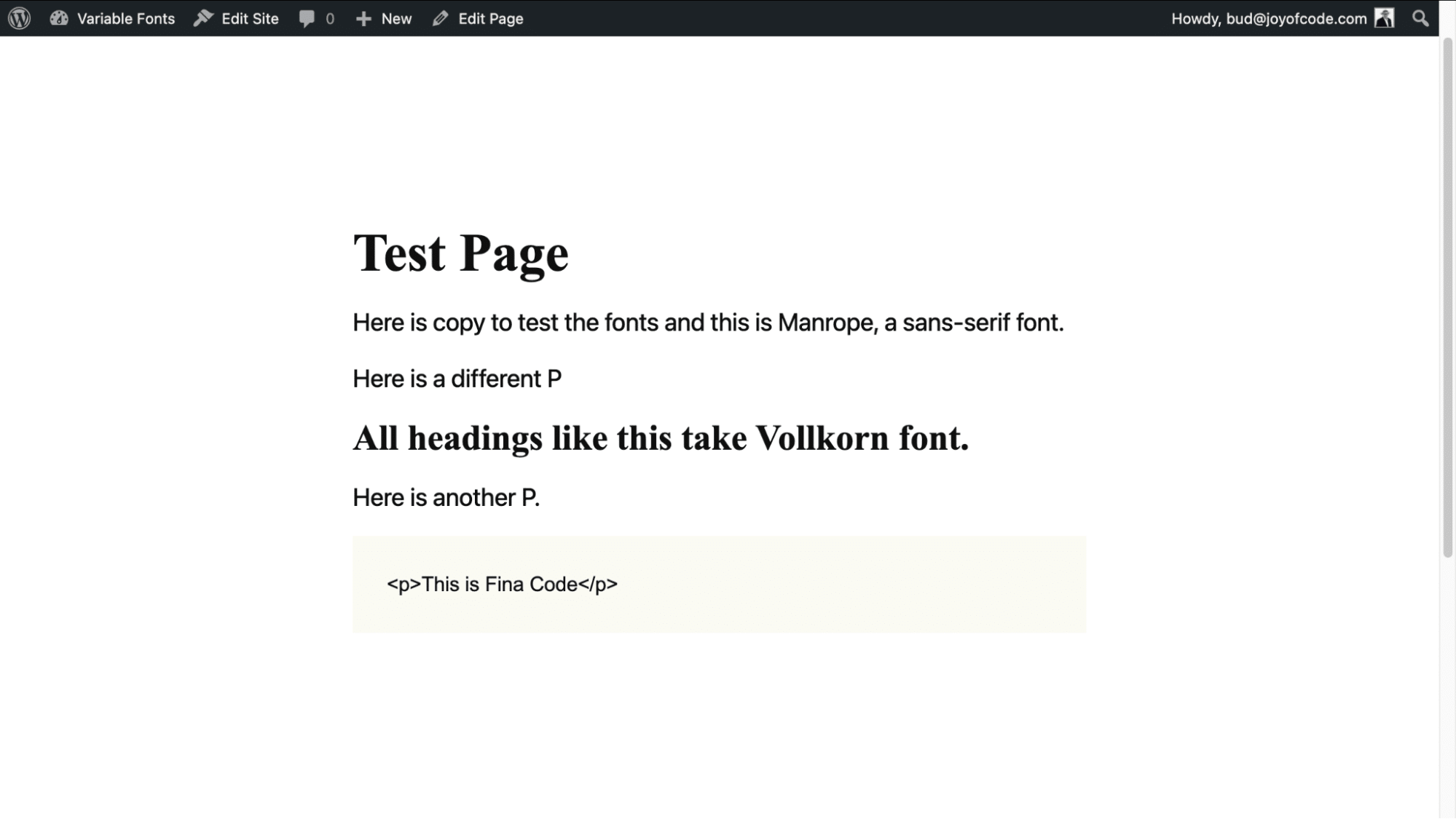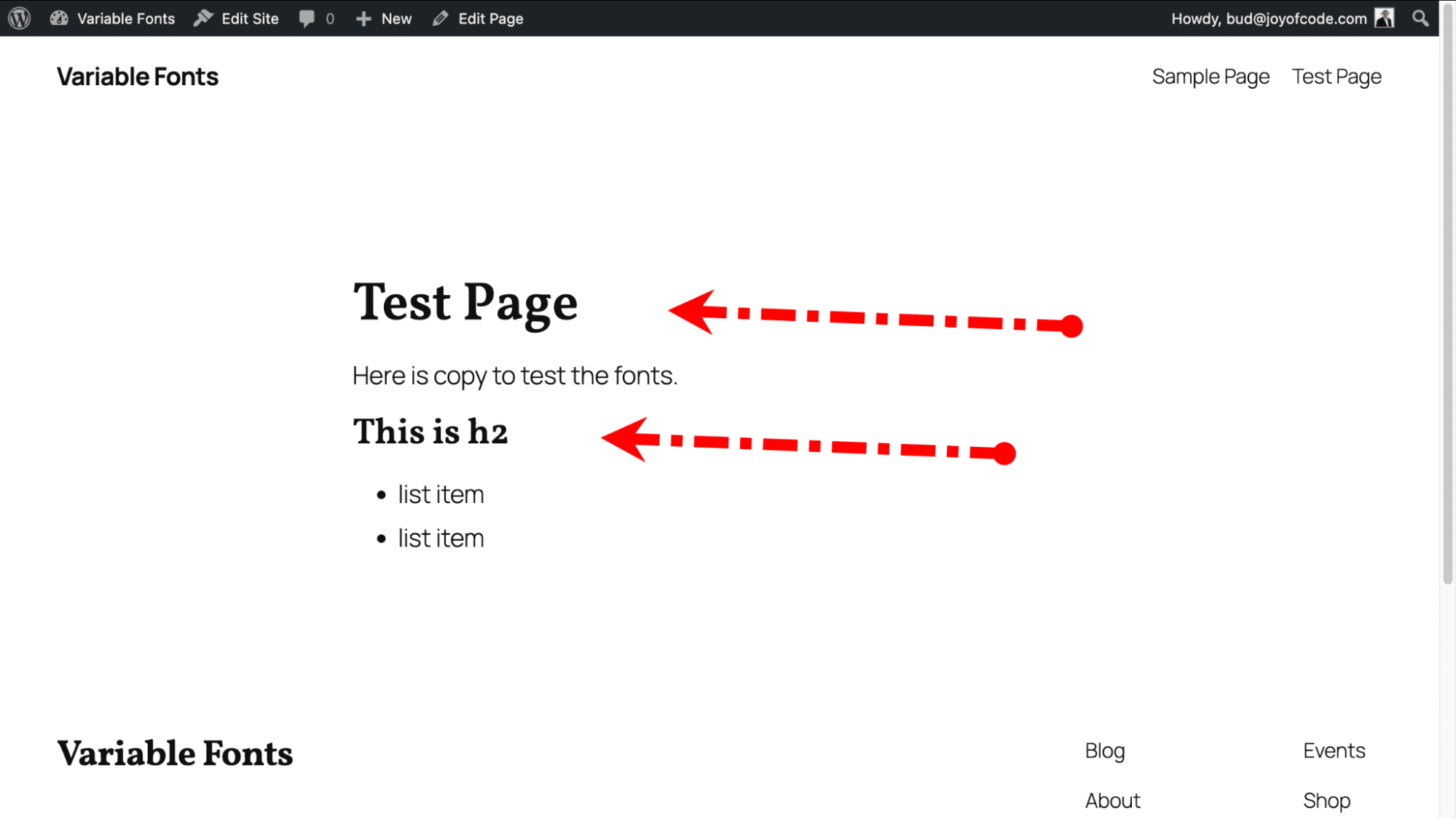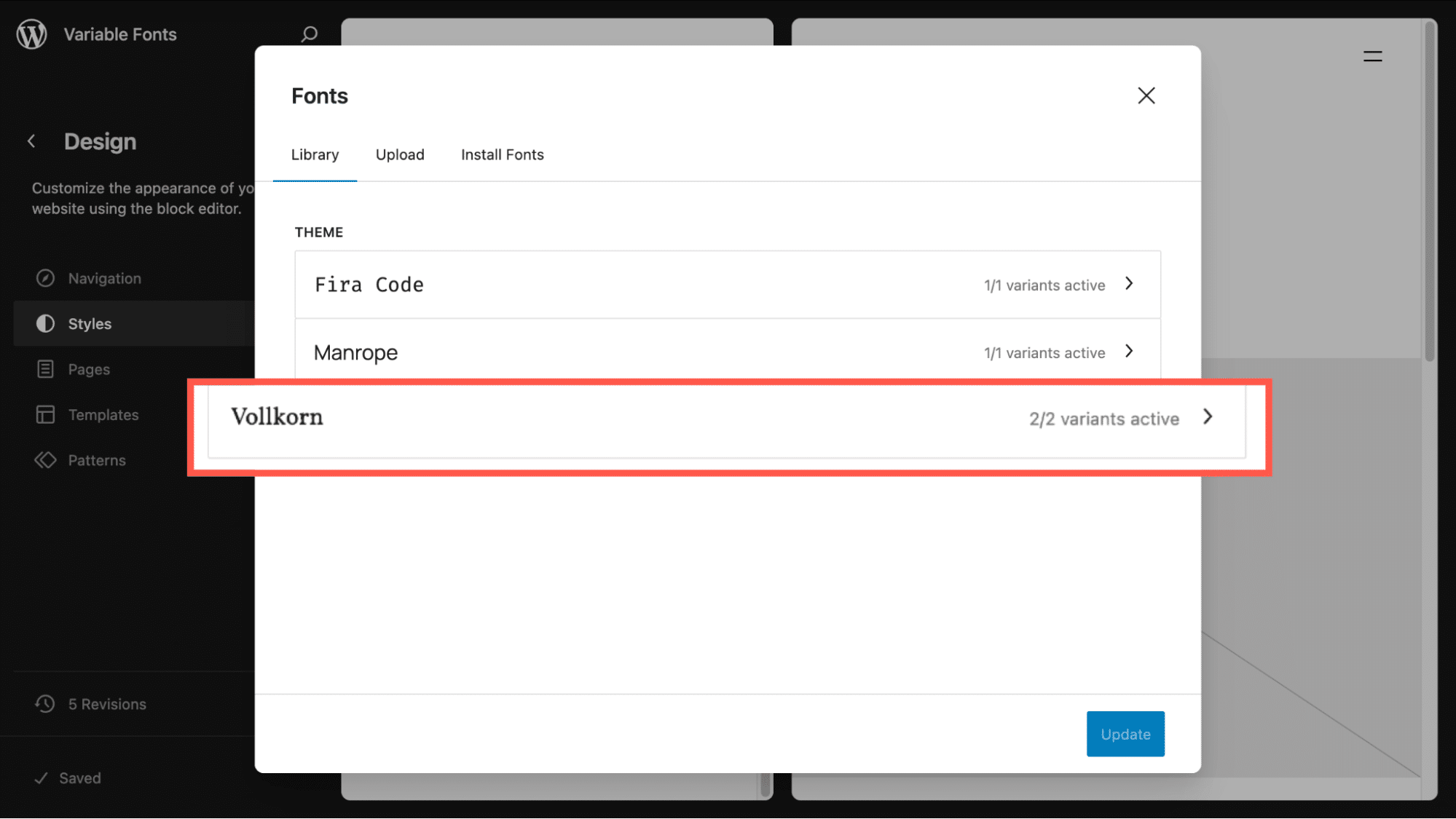
2009年のWebフォント導入以来、ウェブデザインにおけるフォントの自由度は劇的に高まっています。Webフォントは主にCSSの@font-faceルールを使って利用され、システム標準のフォントである「Webセーフフォント」だけに縛られずに済むようになりました。そして、現在もGoogle Fontsを代表とするサービスが多数のフォントファイル形式を提供しています。
これまで、Webフォントを使用する際は太さ(ウエイト)やスタイルごとに別々のファイルを扱い、以下のように、使用時にフォントがどのように表示されるかを明確にする必要がありました。
この方法では、各バリエーションを個々のファイルとして読み込むことでページが重くなり、HTTPリクエストが増え、デザイン作成時のフォント選びと適用が複雑になるというデメリットがありました。
バリアブルフォントとは
2016年にデジタルタイポグラフィの大きな進歩であるバリアブルフォント(可変フォントとも)が登場。Google、Apple、Adobe、Microsoftによって共同開発されたフォントで、すぐに主流になりました。
バリアブルフォントの際立った特徴として、以下の可変要素(axis)をすべてまたは一部を組み込むことができます。
最も広く使われているファイル形式は.woff2(Web Open Font Format)です。2018年にW3C勧告となった非常に圧縮率の高い形式です。.ttfや.otfなどの形式もバリアブルフォントとして使用できますが、.woff2の方が効率的です。またモダンブラウザは全てバリアブルフォントに対応しています。
なお、多くの場合、バリアブルフォントはWebフォントの一種として扱われますが、今回はよりわかりやすく「Webフォント」と「バリアブルフォント」を区別します。
バリアブルフォントを使用するメリット
プロジェクトでバリアブルフォントを使用するメリットは以下の3点が挙げられます。
1. パフォーマンスの向上:複数の別々のフォントファイル(標準、太字、斜体など)を呼び出す代わりに、1つのバリアブルフォントファイルを呼び出せばいいため、HTTPリクエストの数が減り、読み込み時間が短縮されます。
2. デザインの柔軟性:きめ細かな制御が可能なため、font-weight: 500や600に固定される代わりに、532のようなカスタム値を設定できます。
3. レスポンシブ対応:各種デバイスに対応するタイポグラフィを作成できます。例えば、font-weight: clamp()を使ってビューポート間で太さを調整すれば、静的なフォントファイルを使用した際に突然違和感が生じることがありません。
WordPressでバリアブルフォントを使用する方法
2022年11月にリリースされたWordPress 6.1では、theme.jsonシステムにバリアブルフォントのサポートが追加されました。Twenty Twenty-Threeは、最初のバリアブルフォント対応テーマです。
バリアブルフォントを使ったテーマのカスタマイズ
Twenty Twenty-Fiveの子テーマで作業する場合、親テーマと子テーマの両方のスタイルをエンキューすることから始めます。
エディターとフロントエンドの両方でカスタムフォントが一貫して表示されるように、必要な@font-face宣言を含むfonts.cssファイルもエンキューします。
なお、スクリプトのエンキュー方法はテーマによって異なります。
子テーマが適切にセットアップされていることを確認するには、styles.cssで以下のテストを実行します。
theme.jsonでフォントを追加する
Twenty Twenty-Fiveには、デフォルトでManropeとFira Codeの2つのバリアブルフォントが組み込まれています。今回は例としてVollkornを追加し、太さ(ウエイト)600のデフォルトの見出しフォントに設定してみます。
theme.jsonは以下のようになります。
これでサイト全体にVollkornフォントが表示されるようになります。
WordPressフォントライブラリでVollkornが利用可能に
なお、以下の点に注意してください。
• Twenty Twenty-Fiveが更新され、ファイルへの新たなパスが追加された場合を想定して、ManropeとFiraのコードファイルを子テーマにコピーしておくことをお勧めします。
• これらのフォントはすでに親テーマで登録されているため、コードが冗長に思えますが、子テーマで宣言することもお忘れなく。これにより、フォントライブラリUIに正しく表示され、親テーマが新しいファイルパスや変更で更新された場合にも継続して利用できます。
• 上記は2つの異なるVollkornファイルを参照しています。
フォントを適切に読み込むには
CSSでフォントを宣言するまで、フロントエンドでフォントが正しく表示されないことがあります。以下は一般的なstyles.cssです。
子テーマを使用していることをWordPressへの重要なメタデータを含めるには、基本的なstyles.cssファイルが必要になることもお忘れなく。
まとめ
今回ご紹介したいずれの方法を採用するにしても、WordPressのバリアブルフォントは、サイトのタイポグラフィ強化に役立ちます。パフォーマンスを改善し、複雑さを軽減して、従来の静的フォントでは不可能だったレスポンシブで柔軟なデザインを実現することができます。
なお、その可能性を最大限に引き出すには、可変要素(太さ、傾斜、最適サイズなど)を公開するカスタムUIを作成し、サイト所有者が管理できるように配慮する必要があります。